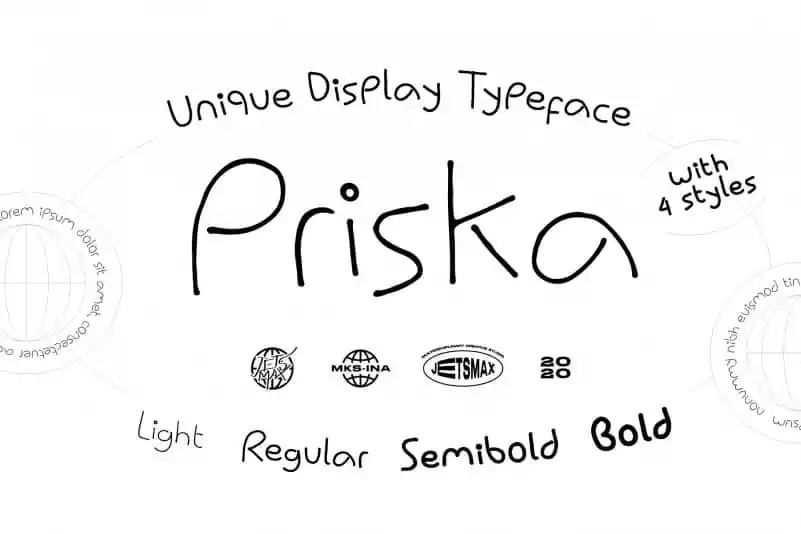
Priska Handwritten Font – Fonte Grátis
Priska Handwritten Font
A Priska Handwritten Font é uma elegante tipografia desenhada à mão, com quatro estilos distintos; Ligeiro, Normal, Semi Bold e Negrito. Esta fonte traz um toque de sofisticação e elegância para projetos de design variados. Seja você designer de moda ou web, gráfico ou publicitário, o Priska Handwritten é uma escolha perfeita para dar à sua obra aquela certa personalidade e charme único. Ideal para elementos visuais que precisam transmitir estilo e elegância através de um texto em destaque. Não hesite em experimentar essa fonte moderna e sofisticada, disponível tanto em estilos leves quanto mais marcantes. Sempre garantindo um resultado final único e inovador no seu trabalho.
Designer: jetsmax